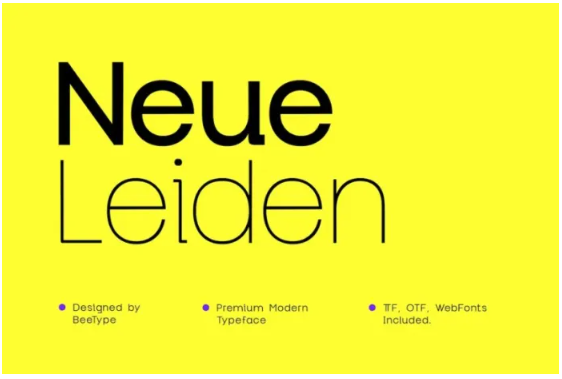
[Elements.Envato] Neue Leiden Typeface (2022)
Neue Leiden - это потрясающий современный шрифт, который может похвастаться чистотой линий. Это чрезвычайно универсальный шрифт, он идеально подходит для логотипов, свадеб, приглашений, цитат, рекламы, печати, журналов и многого другого!
Neue Leiden Display идеально подходит для дизайна, который должен иметь традиционный, старинный вид, но при этом оставаться элегантным и минималистичным. Он будет фантастически смотреться с любым логотипом, названием продукта, плакатом или дизайном.
При его описании на ум приходят такие слова, как элегантный, минимальный, стильный и современный. Он отлично подходит для моды, стилей одежды, подписей, обложек альбомов, журналов, социальных сетей и рекламы. Этот шрифт имеет 200 вышеуказанных глифов и широкую поддержку латинского шрифта, а также символов верхнего и нижнего регистра sans serif. Он несет в себе мощную, уникальную и социальную линию символов с премиальной отделкой, создающей новое впечатление. Элегантный, аутентичный и тонкий шрифт с засечками. Neue Leiden - это 7 вариантов шрифта.
Neue Leiden - это потрясающий современный шрифт, который может похвастаться чистотой линий. Это чрезвычайно универсальный шрифт, он идеально подходит для логотипов, свадеб, приглашений, цитат, рекламы, печати, журналов и многого другого!
Neue Leiden Display идеально подходит для дизайна, который должен иметь традиционный, старинный вид, но при этом оставаться элегантным и минималистичным. Он будет фантастически смотреться с любым логотипом, названием продукта, плакатом или дизайном.
При его описании на ум приходят такие слова, как элегантный, минимальный, стильный и современный. Он отлично подходит для моды, стилей одежды, подписей, обложек альбомов, журналов, социальных сетей и рекламы. Этот шрифт имеет 200 вышеуказанных глифов и широкую поддержку латинского шрифта, а также символов верхнего и нижнего регистра sans serif. Он несет в себе мощную, уникальную и социальную линию символов с премиальной отделкой, создающей новое впечатление. Элегантный, аутентичный и тонкий шрифт с засечками. Neue Leiden - это 7 вариантов шрифта.